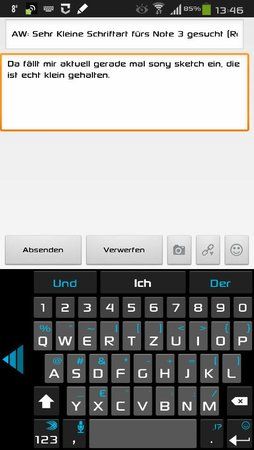
Sehr Kleine Schriftart fürs Note 3 gesucht (Root vorhanden)
Hi. Die Standard Schriften im Note 3 sind mir selbst auf der sehr klein Einstellung noch zu groß. Kennt jemand eine Schriftart die sehr klein ist und z. B. "Nachrichten" nicht mit "Nachricht.." Abkürzung sondern unten in der leiste korrekt aufschreibt?
Bitte aber kein geschnörkel wie Eisenach etc... Eine schöne Standard Schriftart ähnlich der von Samsung selbst.
Da fällt mir aktuell gerade mal sony sketch ein, die ist echt klein gehalten.